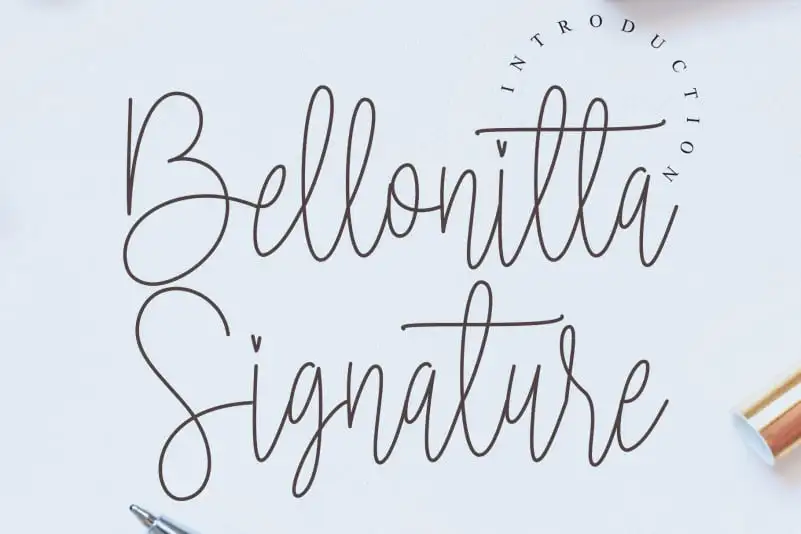
Bellonitta Signature Script Font – Download Grátis
A Bellonitta Signature Script Font é uma delicia para os olhos que traz nuances sutis e texturas interessantes à sua tipografia. Escrevendo com essa fonte, você vai capturar instantaneamente a atenção de seu público-alvo, seja no design gráfico, na publicidade ou em qualquer material de marketing digital. Com uma caligrafia natural e única, ela proporciona um toque autêntico que destaca o conteúdo. Este é mais do que apenas uma fonte: ele é um ativo visual poderoso que eleva seu projeto a outro nível. Através da Bellonitta Signature Script Font de CreativeLetter, você cria um design gráfico envolvente e natural que captura a atenção imediatamente. A fonte apresenta traços leves e finos, combinados com texturas suaves e detalhes exóticos que criam uma experiência única. É ideal para anúncios de marketing digital, como nome do site ou página de produto, design de produtos, banners publicitários ou qualquer outro trabalho gráfico em que você deseje adicionar um toque único e autêntico. A criação com essa fonte é uma aventura visual, onde cada letra parece ter sido escrita por mão humana, garantindo sempre a máxima atenção do seu público. A Bellonitta Signature Script Font não apenas oferece uma experiência de leitura confortável para os usuários finais, mas também se destaca como um item de design que adiciona valor ao seu trabalho.